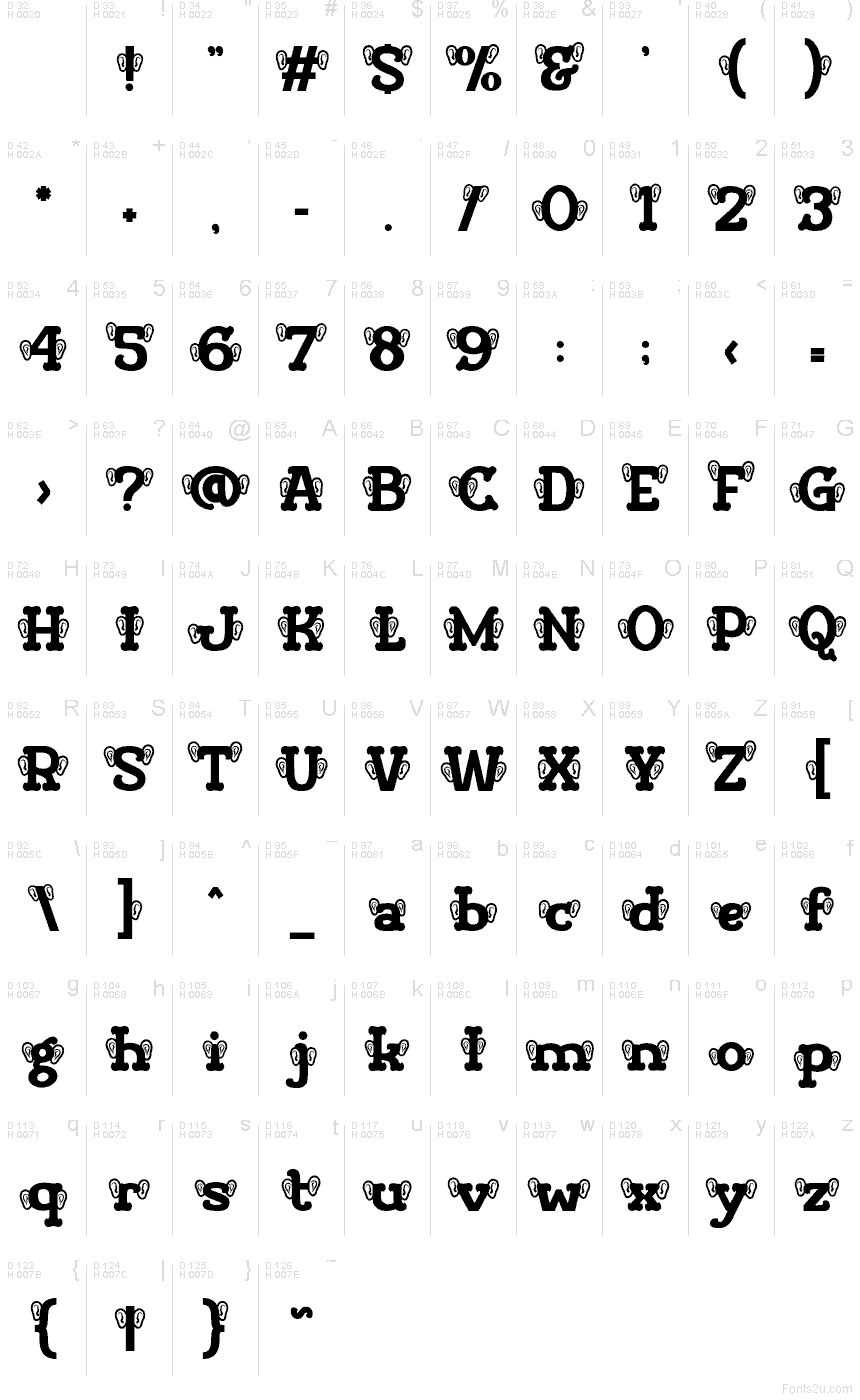
Visage Face Five von Putracetol Studio ist eine kostenlose, anthropomorphe Display-Schrift, die ein skurriles, gesichtsähnliches Konzept direkt in die Buchstaben integriert. Schwere, schwarze Formen treffen auf abgerundete, klobige Silhouetten, während sich wiederholende, comicartige Ohren das Alphabet in eine Ansammlung von Charakteren mit einer leicht exzentrischen, verspielten Stimmung verwandeln.
Dadurch fühlt sich diese Schrift besonders wohl bei Plakatüberschriften, Grafiken für Kinderveranstaltungen, Sticker-Designs, YouTube-Thumbnails und Merchandising-Artikeln, bei denen das Ohren-Motiv sofort ins Auge fällt. Sie eignet sich zudem hervorragend für kurze Headlines und Monogramme, da die Buchstaben eher wie kleine Maskottchen als wie neutrale Schriftformen wirken.
Visage Face Five